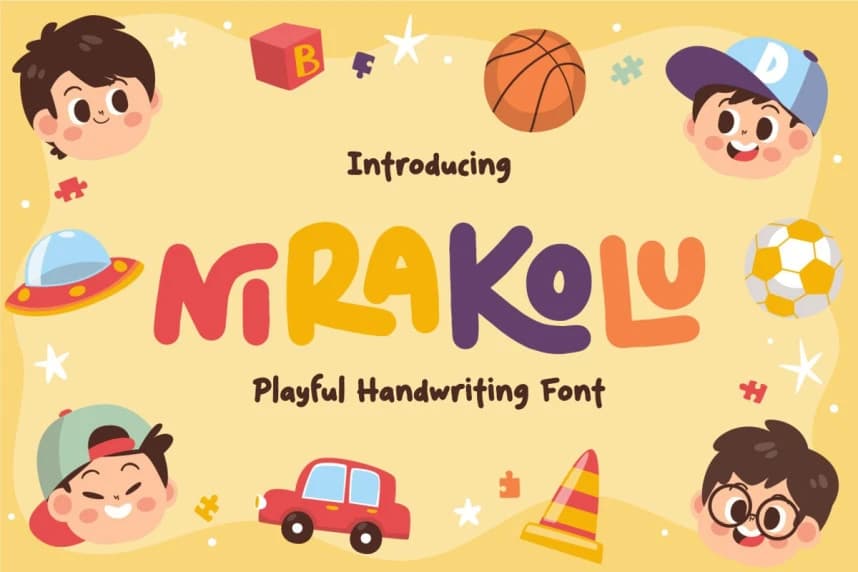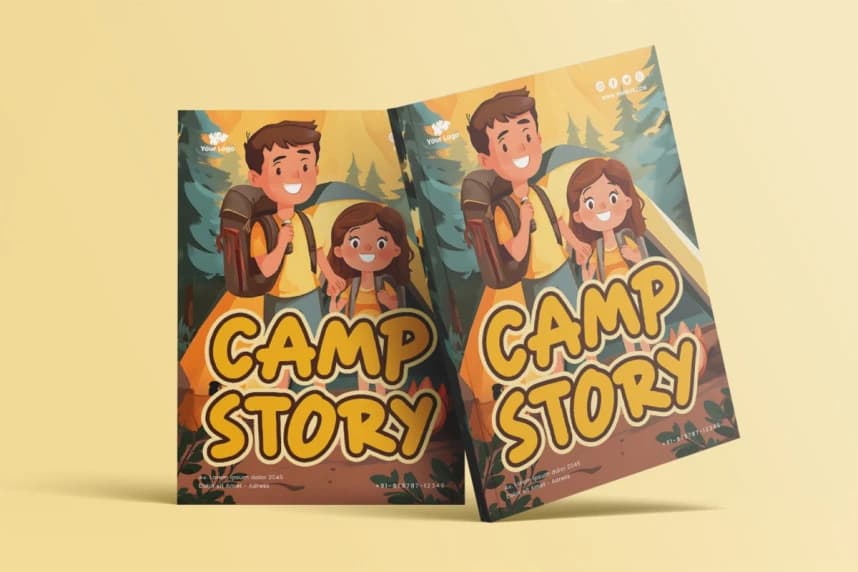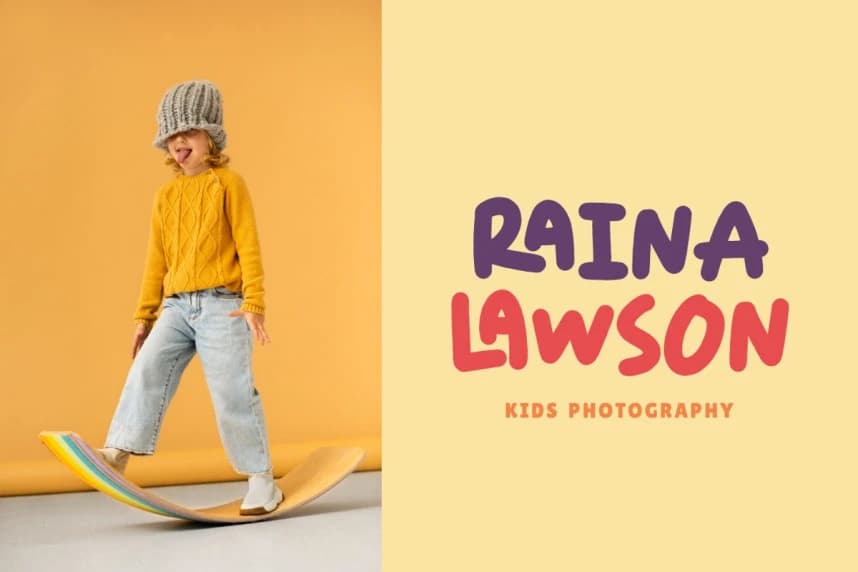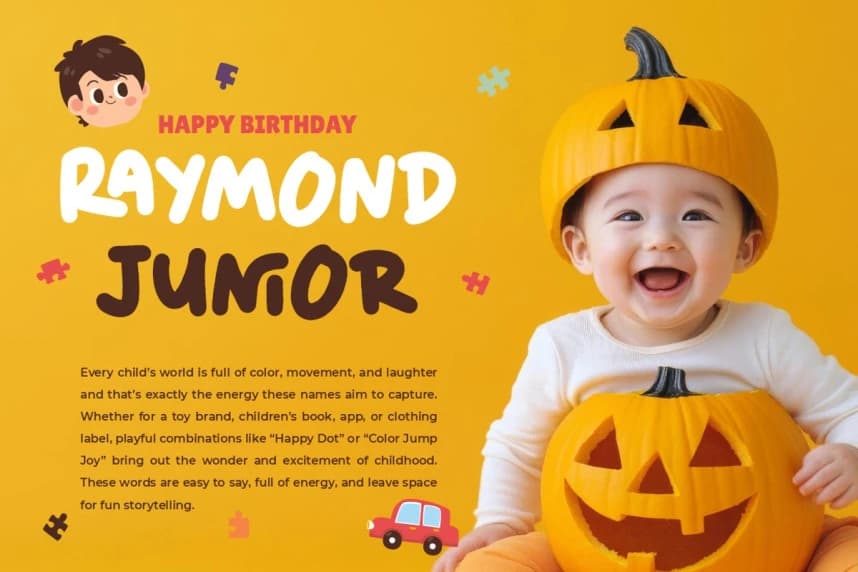
Nirakolu Playful Font
Nirakolu Playful Font, çocukluğun kaygısız ruhunu ve oyuncu karalamaları yakalayan neşeli bir yazı tipidir. Karakterler cesur ve yuvarlak hatlıdır; yükseklikleri hafifçe düzensiz olduğundan her harfe canlı, el yapımı bir dokunuş verir.
Nirakolu Playful Font, çocukluğun kaygısız ruhunu ve oyuncu karalamaları yakalayan neşeli bir yazı tipidir. Karakterler kalın ve yuvarlaktır; yükseklikleri hafifçe değişkendir, bu da her harfe canlı bir el yapımı dokunuş katar.